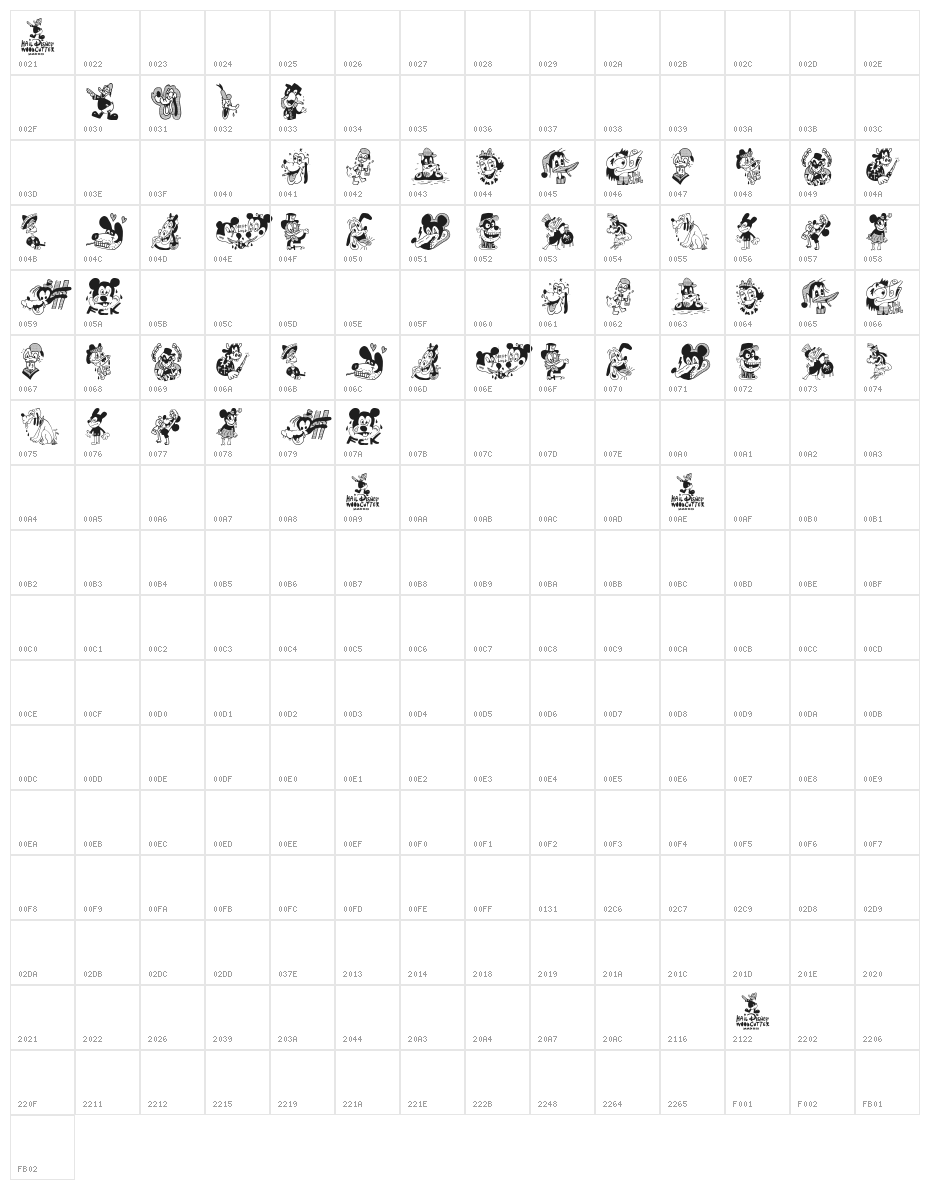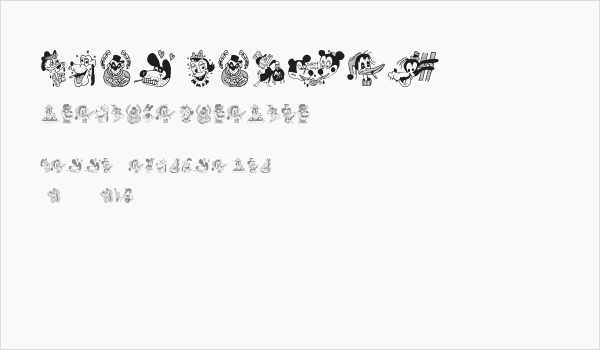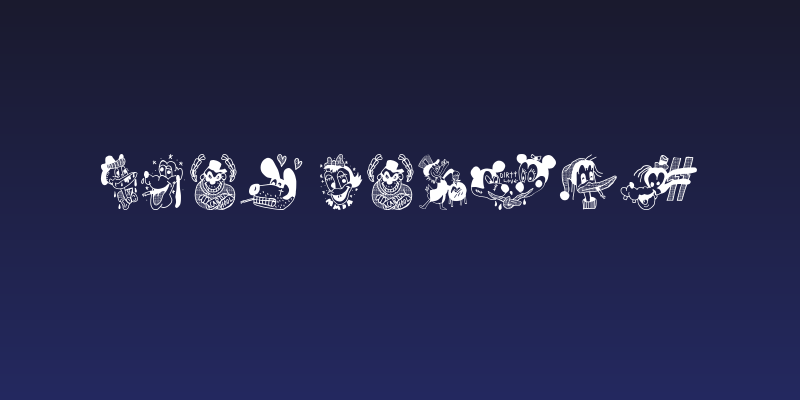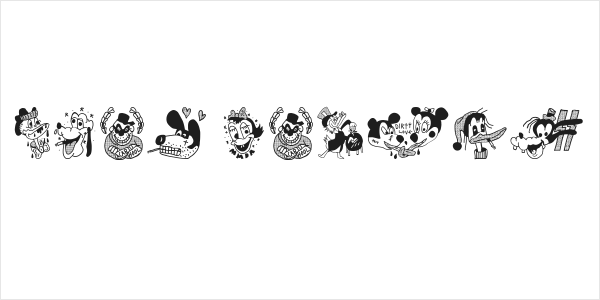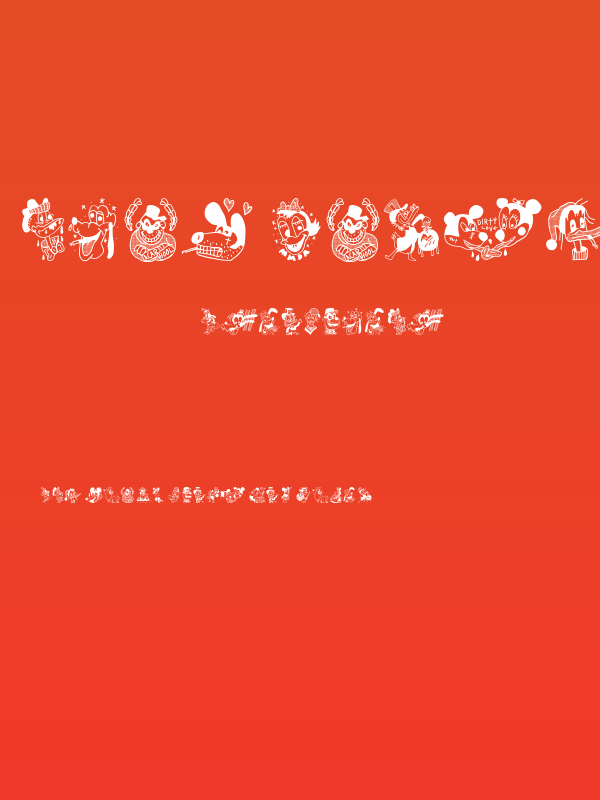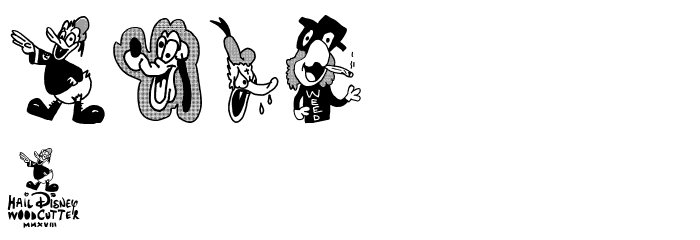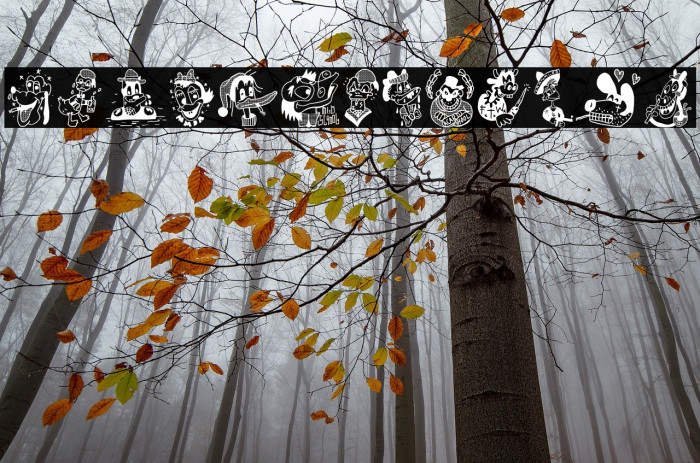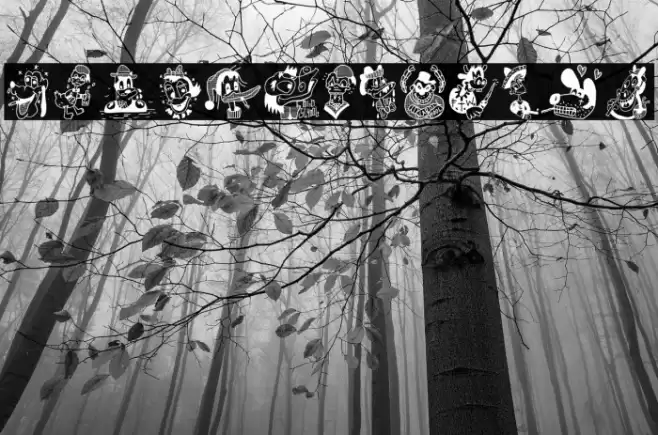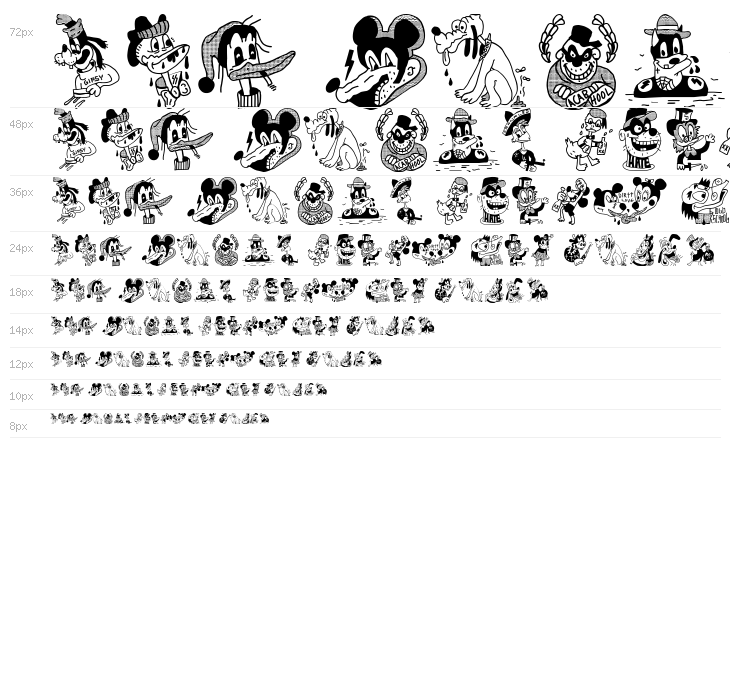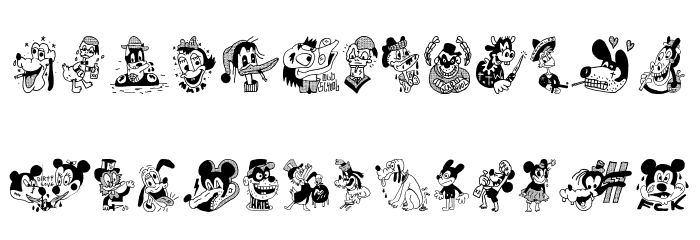
Hail Disney Font
| 全体的なスタイル | Vintage, Cartoon |
| 用途 | Decorative illustrations, Themed projects, Merchandise |
| おすすめプロジェクト | Ideal for use in graphic novels, animation projects, themed merchandise, or as decorative elements in design projects that aim to evoke a sense of nostalgia and playfulness. |